09C 呉竹体の変形——羅篆形・フワンテル形・ラウンドゴチック形
欧字書体としてのラテン(Latin)、ファンテール(Fantail)、ラウンド・ゴシック(Round Gothic)は装飾用の書体とされている。漢字書体もおそらくは装飾用として用いられるものと思われる。
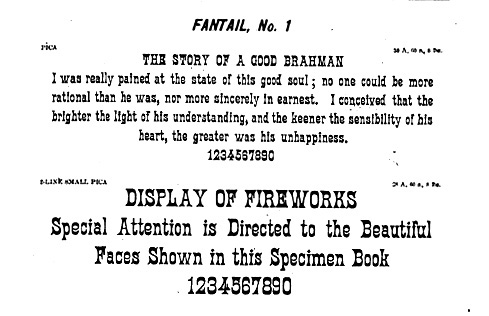
『参號明朝活字総数見本』(1928年 東京築地活版製造所)は、その名のとおり三号サイズの明朝活字の総数が掲載されているが、それに加えて「ゴチック形」とともに「フワンテル形」と「羅篆形」の見本も掲載されている。
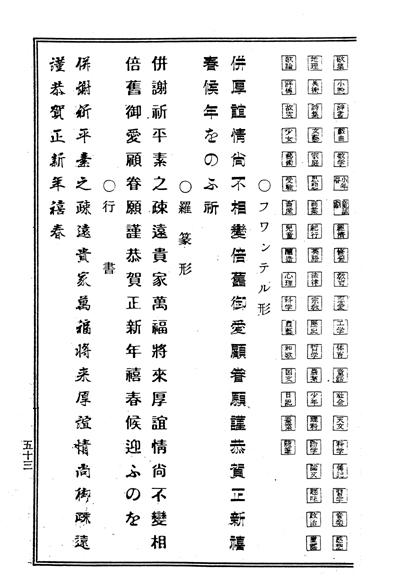
図版:『参號明朝活字総数見本』(1928年 東京築地活版製造所)
青山進行堂『富多無可思』(1909年)には電話用活字として四号ラウンドゴチック形が掲載されている。秀英舎の『活版見本帖』(1914年)には初號丸形ゴヂックを見ることができる。この「ラウンドゴチック形」「丸形ゴヂック」が丸ゴシックの源流にあたるのではないかと思われる。
青山進行堂では、1916年(大正5年)3月に「篆書ゴシック体」を発表して注目を集めた。これによって、篆書体とゴシック体(黒体)との出会いがあったことがわかる。
『活版総覧』(1933年、森川龍文堂活版製造所)の44ページには、「五號丸ゴチック」と「五號天書(篆書)」が掲載されているが、わざわざ次のように注がつけられている。
(丸ゴチックと篆書は少しの違ひであります)
このふたつを比較してみると、どちらも現在各社で販売されている円体(丸ゴシック体)と書法芸術の篆書との間に位置するようである。
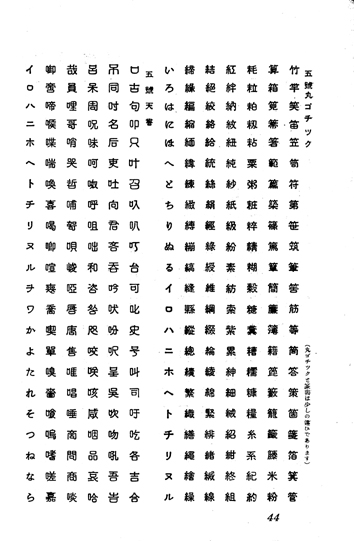
図版:『活版総覧』(1933年、森川龍文堂活版製造所)
「フワンテル形」は「ゴシック形」の縦画を細めたスタイル、「羅篆(ラテン)形」は「ゴシック形」の横画を細めたスタイルだ。装飾的な脚色はありますが、基本は「ゴシック形」からのヴァリエーションだと思われる。
「フワンテル形」の完成された書体として「石井ファンテール」(1937年、株式会社写研)があげられる。また「羅篆(ラテン)形」としては「アポロA2」(1969年、株式会社モトヤ)がこれに近い。
「ラウンドゴチック形」は、「丸ゴシック体」として各社から多くの書体が発売されている。